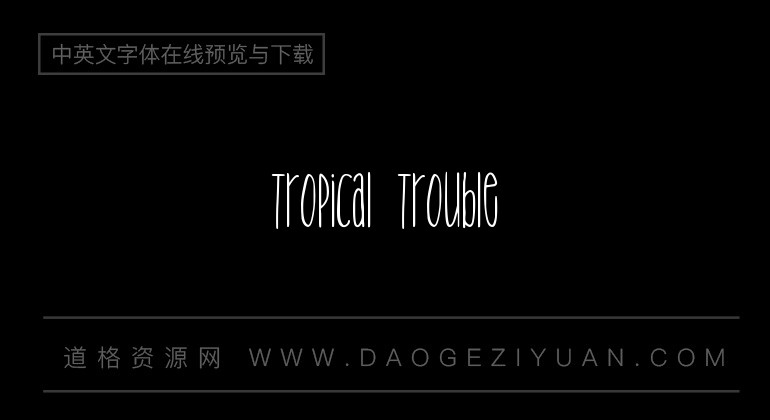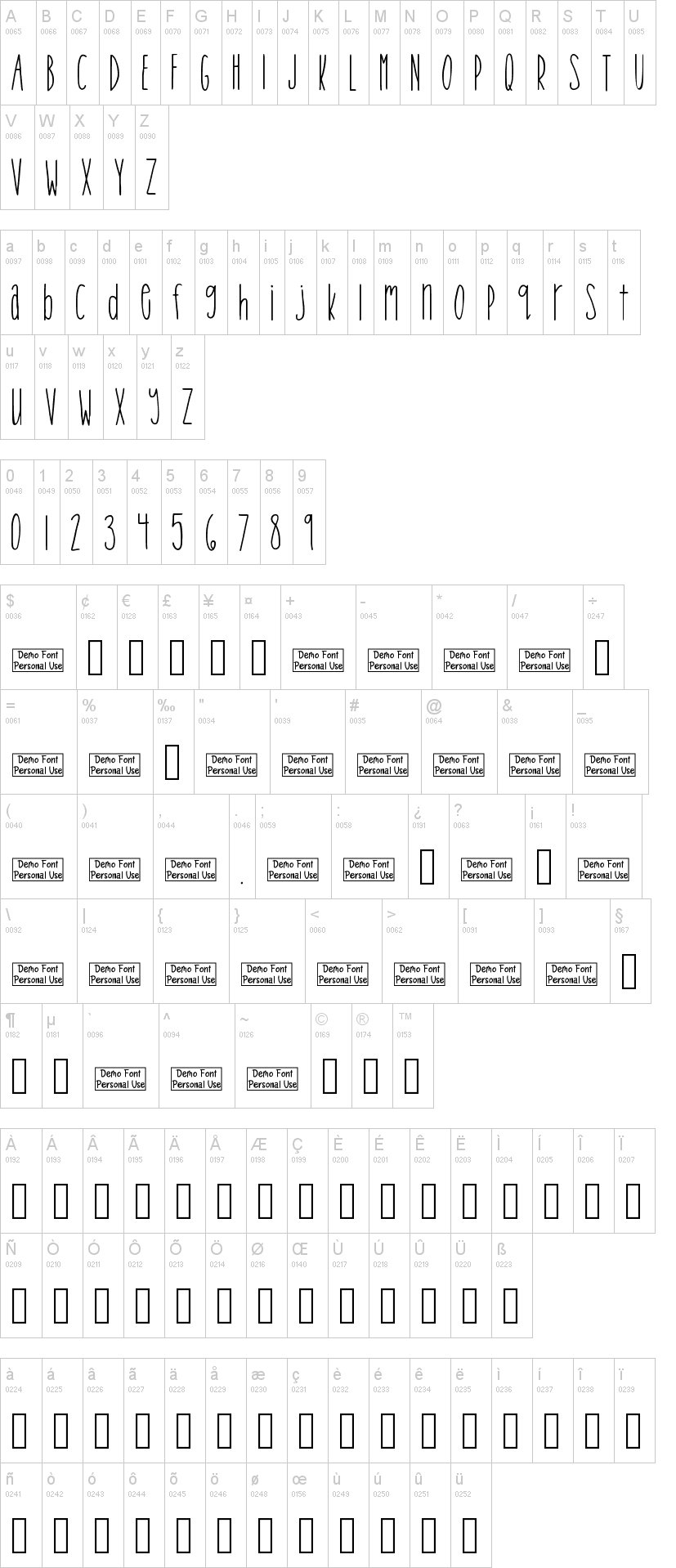
Tropical Trouble
? Tropical Trouble 是一款极具特色的字体,它具有海洋风格,拥有细腻的线条,可以提供清新活泼的视觉体验。它可以用于海洋类的标识、海洋风格的网站或者海洋风格的印刷品,也可以用于更加活泼的标题和插图。此外,它还具有英文和拉丁文字体,能够满足不同的需求。
Tropical Trouble是一款非常不错的手写艺术字体,具有很好的视觉感,适合于文化类的宣传设计、商业类品牌的广告和产品包装设计以及个性化文字排版等较多场景。
Tropical Trouble字符映射图